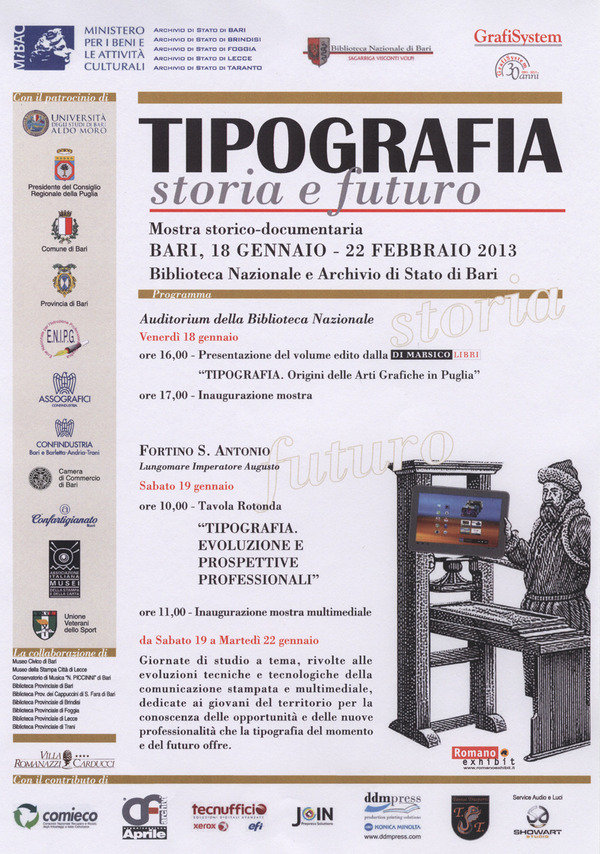
Bari, ''Tipografia. Storia e futuro'' alla Biblioteca nazionale e al Fortino Sant'Antonio
BARI - Si inaugura venerdì 18 gennaio alle 17.00 nell'Auditorium della Biblioteca nazionale di Bari "Tipografia. Storia e futuro", mostra storico-documentaria che ripercorre le fasi dello sviluppo dell'arte tipografica in Puglia attraverso documenti originali, volumi, pannelli didascalici, materiale fotografico, oggetti e attrezzature d'epoca, e che sarà aperta al pubblcio sino a venerdì 22 febbraio.
Sabato 19 gennaio dalle 10.00, inoltre, presso il Fortino Sant'Antonio è in programma una tavola rotonda sul tema e l'inaugurazione della mostra multimediale.